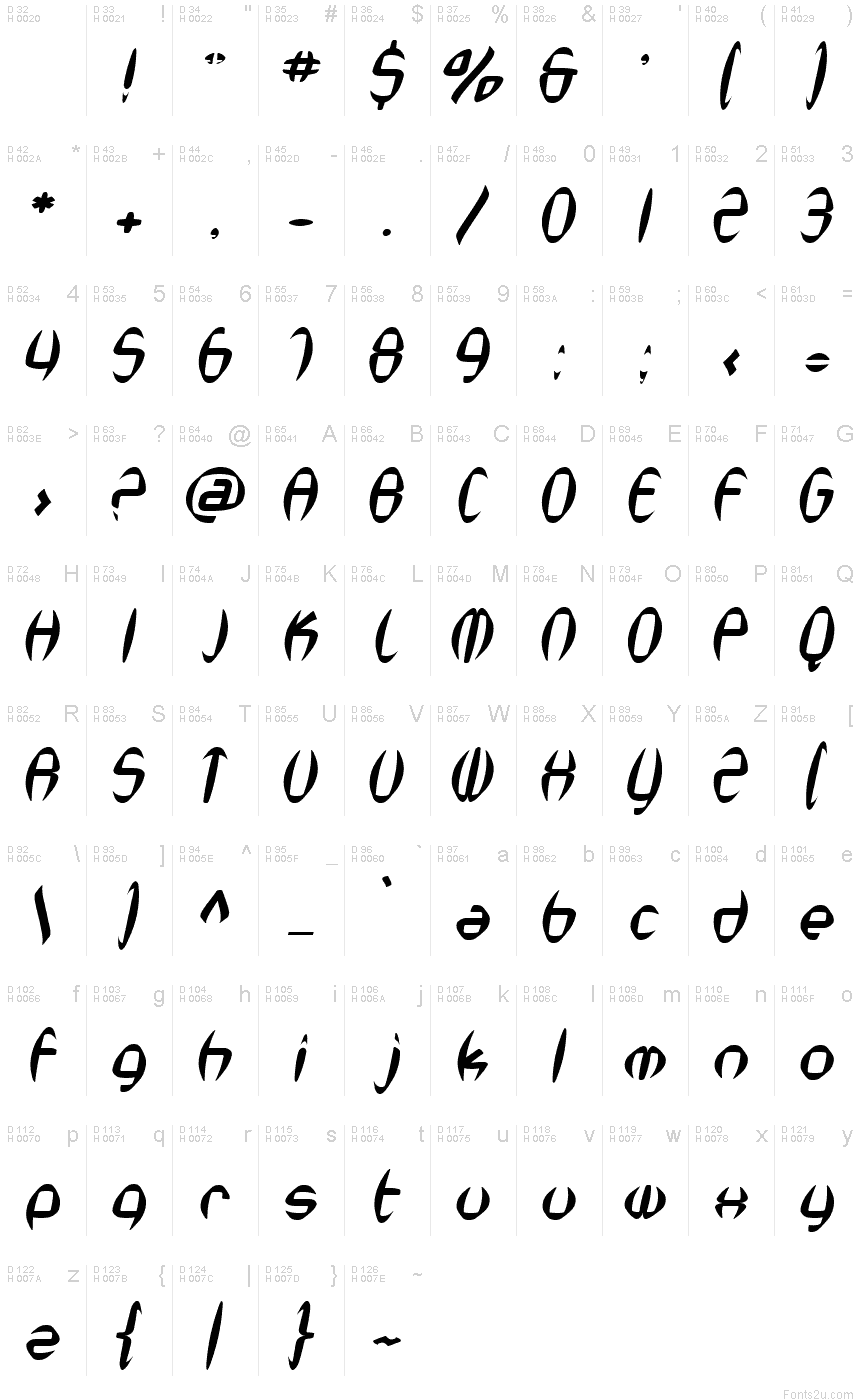
SF Synthonic Pop Oblique von ShyFoundry ist eine kostenlose Sci-Fi-Display-Schrift mit einem eleganten, futuristischen Flair des späten 20. Jahrhunderts. Die Buchstaben wirken wie durch Bewegung geformt und verbinden weiche, geschwollene Kurven mit scharfen, hakenförmigen Spitzen. Das verleiht dem Alphabet einen synthetischen, aerodynamischen Zug, ganz ohne den starren Tech-Look.
Das macht sie zu einer perfekten Wahl für Cover von elektronischer Musik, Retro-Future-Poster, Game-Titel, Club-Flyer und kompaktes Branding, bei dem ein paar Wörter ein stylisches Signal setzen sollen. Als kostenlose Schrift eignet sie sich am besten für kurze Schlagzeilen, Logos und Cover-Texte, da die geschwungenen Schnitte und dynamischen Kurven bei kurzen Phrasen besser zur Geltung kommen als bei langen Textblöcken.